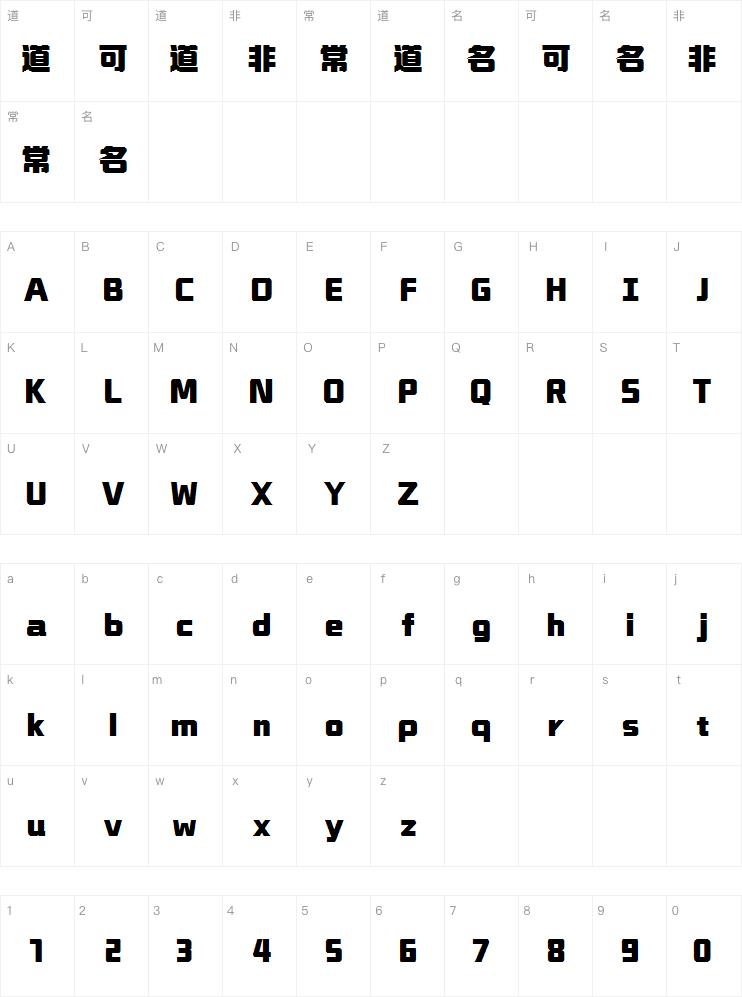
山海明净黑w
山海明净黑,是一款全新的字体,包含汉字9169个,符号200+个。该字体是一款综艺标题黑体字体,是一款具有强劲视觉冲击力的综艺风格标题字体。字形充实填满整个字框,造型硬朗,同时兼顾圆润性。直线与圆弧的笔画构成坚实有力,拥有宽大的中宫、粗厚且直线化的笔画设计、简洁明了的笔画切角,带来强有力的视觉冲击效果。该字体在综艺体的基础上做了诸多创新,使得字形带有律动感,让该字体既有着流动的美感,又有着端肃的凝重,在正式用字场合落落大方,在日常使用环境中不失亲切友好,能够在保留综艺体基本特征的基础上更能适应当下时尚潮流的需要,助力各大新产品夺取标题主战场。